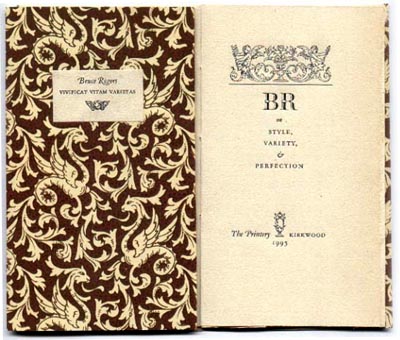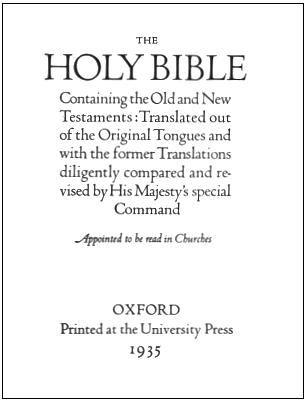
Bruce Rogers (1870 - 1957)O seu colega Updike considerou que Bruce Rogers era the most distinguished designer of books of our time. De facto, ele interessou-se prioritariamente por livros e só secundariamente por typefaces.
Com apenas 16 anos, o norte-americano Bruce Rogers começou a estudar Arte na Purdue University em Lafayette, e em breve se tornou destro calígrafo. Começou a trabalhar para J.M. Bowles, editor da revista Modern Art. Em 1896 foi apontado para director artístico da Riverside Press, editora para a qual trabalhou nos próximos seis anos. A partir de 1912, trabalhou como designer freelance para clientes como Alfred Knopf, Pynson Press, Lakerside Press e outros. Em 1916, Bruce Rogers mudou-se para o Reino Unido, para trabalhar junto a Sir Emery Walker na Mall Press, onde compôs e imprimiu pessoalmente uma selecta colecção de cópias de Sobre a forma da letra de Dürer, tarefa completada em 1917. Em 1917 foi apontado para Conselheiro Tipográfico da University of Cambridge Press; é aqui que se apercebe da alta qualidade da tipografia inglesa. Surge o seu entusiasmo pelos tipos de John Baskerville, que tinha descoberto na magnífica impressão que este fez da Bíblia. Durante a sua estância em Cambridge, Rogers também desenhou um tipo para os posters da Meynells Pelican Press, mas o defralgar da I. Guerra impediu a sua edição comercial.
Em 1919 regressou aos E.U.A. e começou a desenhar livros para William E. Rudge. Nesta sequência realizou a Oxford Lectern Bible, obra-mestra da tipografia revivalista do século XX. Ao mesmo tempo imprimiu a Bíblia que John Baskerville realizou em 1763 e que tão profundamente o tinha impressionado. Durante a sua estadia no Reino Unido, de 1928 a 1932, Rogers produziu dois dos seus melhores livros: a Oxford Lectern Bible e The Odyssey (1932). Depois de regressar aos EUA, Rogers estableceu-se na sua casa em New Fairfield. Desenhou alguns livros para o Limited Editions Club of New York - entre eles a edição in-fólio em 37 volumes das obras de Shakespeare, e mais outra Bíblia. Morreu em 1957. PublicaçõesRogers, Bruce. Report on the Typography of the Cambridge University Press. Cambridgeshire: University Printer. Cambridge, 1950. Elaborado em 1917 e impresso por ocasião do 80.º aniversário de Bruce Rogers, em 1950, por Brooke Crutchley. Fontes
Bruce Rogers desenhou o seu primeiro tipo Montaigne em 1902, para a Riverside Press. Este typeface, inspirado na letra de Nicolas Jenson, foi gravado em metal por Robert Wiebking em 16 pontos. Em 1909 desenhou uma versão do typeface de William Caslon I o Riverside Caslon. Em 1914, Rogers desenhou a fonte Centaur para o New York Metropolitan Museum, tipo depois editado em 1929 pela Monotype. A Centaur MT é uma vigorosa reinterpretação da romana de Nicolas Jenson. A versão digital está bem equipada com ligaduras e glifos alternativos. Como Jenson não usou itálicas, o fino corte cursivo orienta-se pelo modelo de Francesco Griffo e de Ludovico Degli Arrighi. Ao longo de 90 anos de uso, a Centaur MT não perdeu nada do seu brilho original, concorrendo com qualquer nova fonte desta classe. A fonte Centaur foi buscar o seu nome ao livro The Centaur, de Maurice de Guérin, publicado em 1916 pela Montague Press de Massachusetts. Esta edição de 135 exemplares mostra pela primeira vez o tipo desenhado por Bruce Rogers. Por volta de 1900, Rogers foi encarregado do design de livros da Riverside Press em Cambridge, Massachusetts. Numa exposição na Boston Public Library viu um exemplar de De Preparatione Evangelica, de Eusebio, livro impresso em 1470 por Jenson. Quis recriar o tipo de Jenson; a pesquisa que se seguiu foi como «a busca daquilo que eu pensava profundamente ser o tipo idealmente perfeito, não sabendo então que era algo como a busca do Santo Graal». A primeira versão da Centaur foi a Monotype Centaur. O corte itálico foi desenhado por Frederic Warde em 1925, a partir do desenho das letras de Ludovico Degli Arrighi, um escriba renascentista cujas letras estão entre as melhores cursivas chancelerescas. A fonte Arrighi foi editada, em 1929, pela Monotype para acompanhar a Centaur.